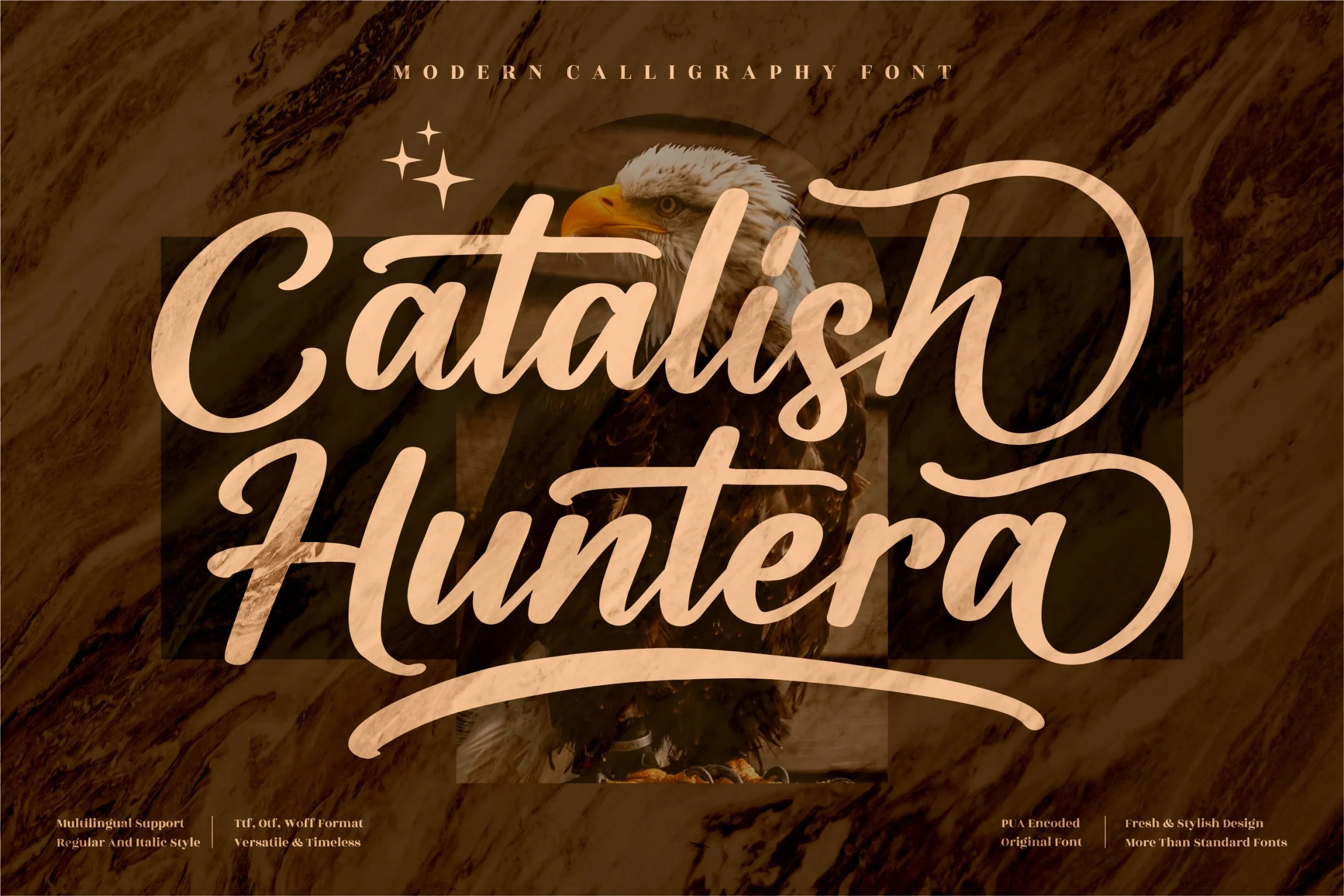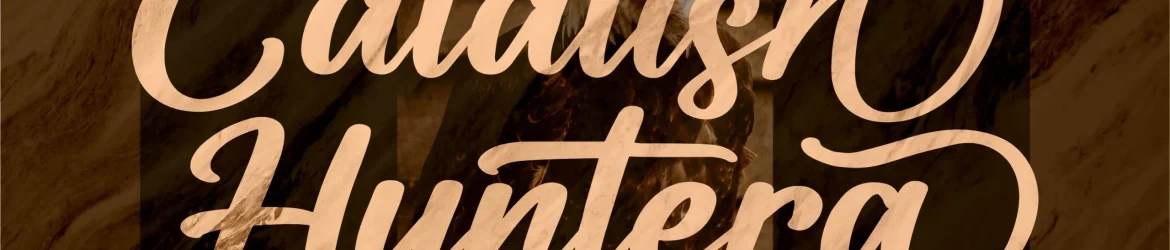
Catalish Huntera Font – Download Grátis
Esta é uma fonte de assinatura premium perfeita para um amplo espectro de projetos que requerem um sabor de assinatura de luxo. Afonte “Catalish Huntera Font” está disponível para seus projetos, independentemente da área que você trabalha. Com seu design elegante e detalhado, esta fonte é perfeita para criar logotipos, embalagens personalizadas de produtos, etiquetas em compras, cartões de nome, convites, cartões de agradecimento, capas de livros, camisetas com mensagens, posters de eventos especiais e muito mais. Ela é ideal para qualquer projeto que necessite de um toque único e sofisticado, seja ela uma camisa casual ou uma arte em papel dourado para um livro raro. Seja você criando sua própria identidade visual ou fazendo design de embalagens personalizadas, “Catalish Huntera Font” é a escolha perfeita.